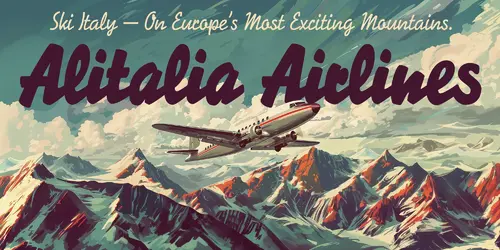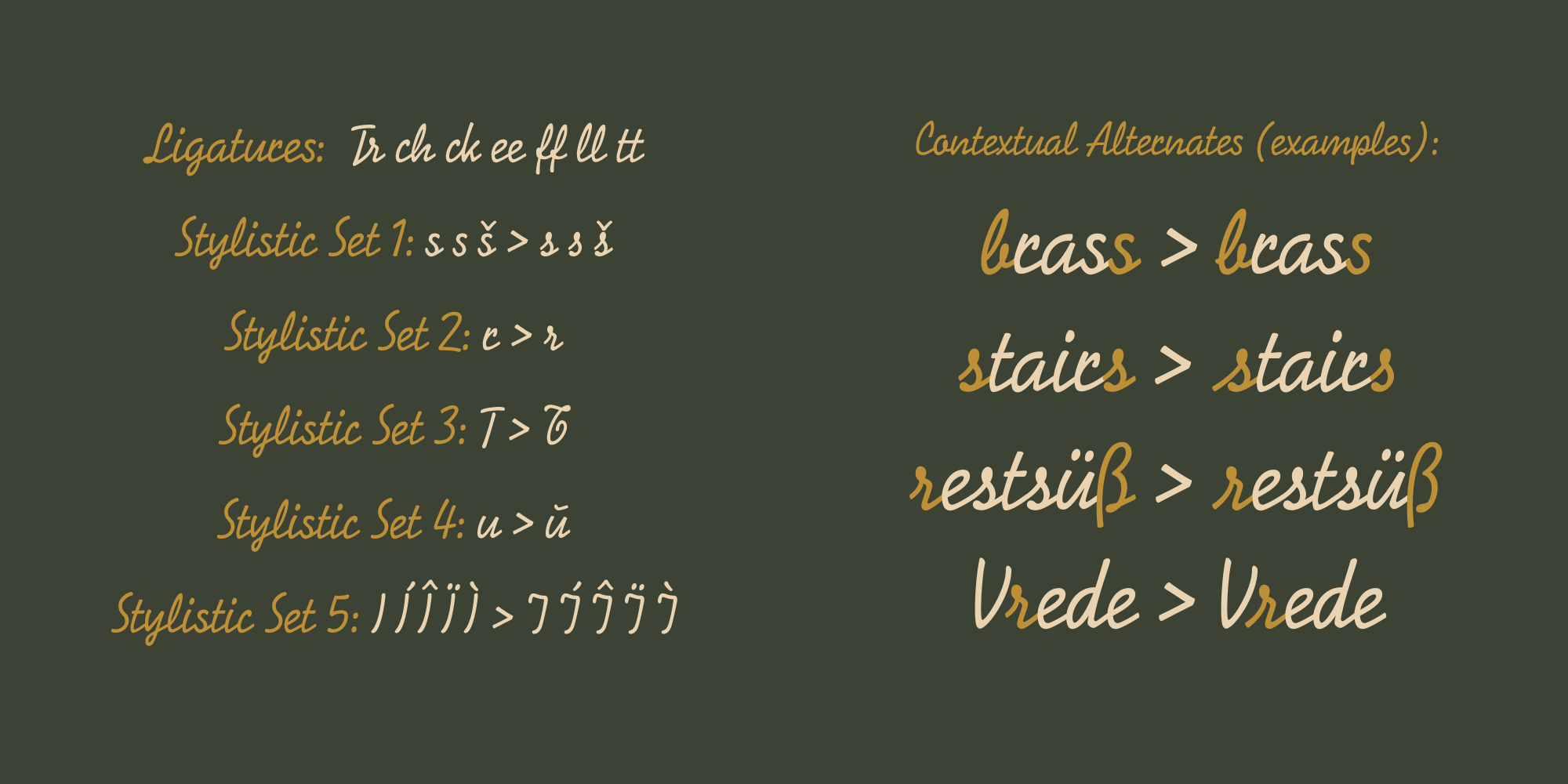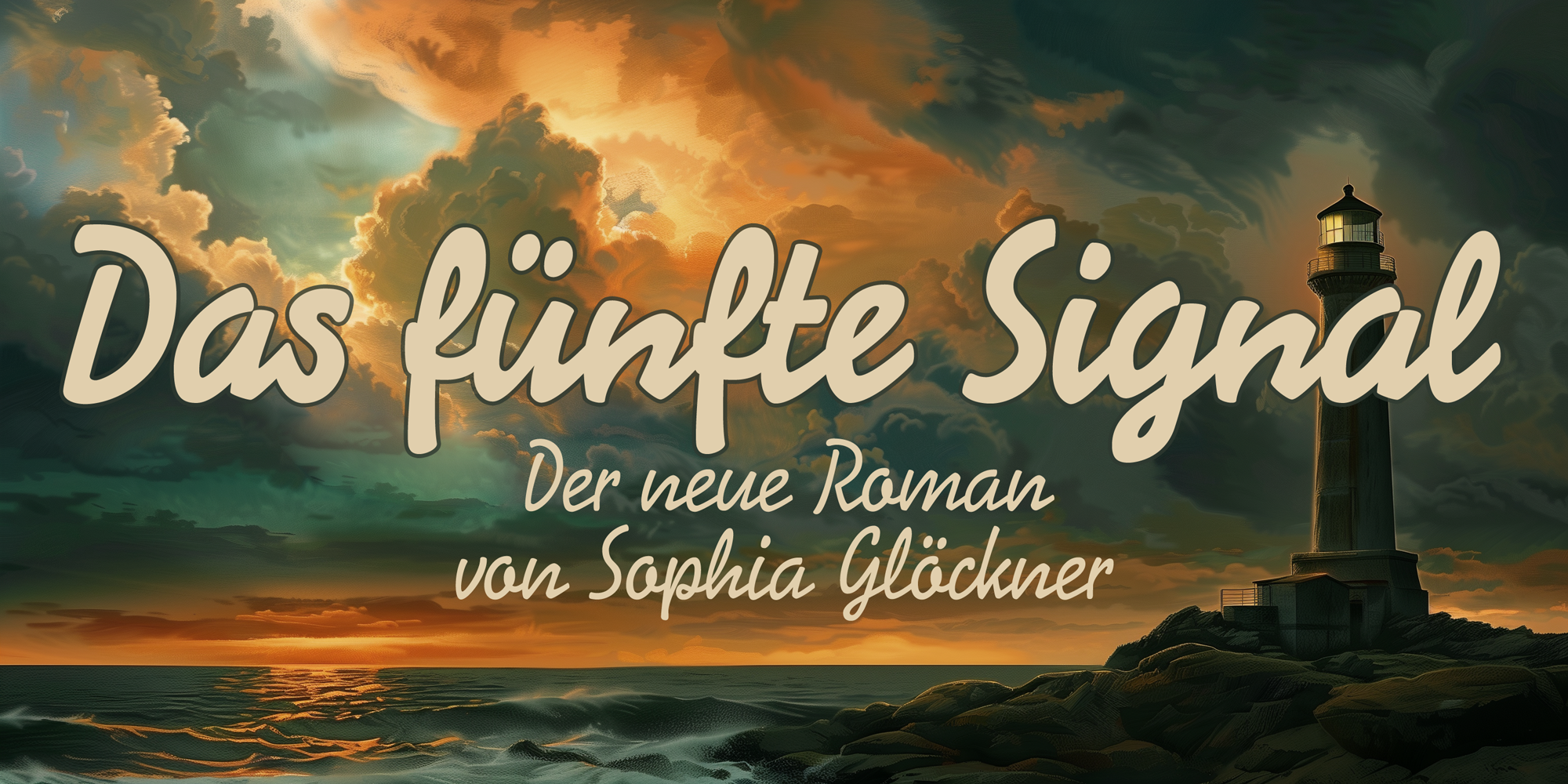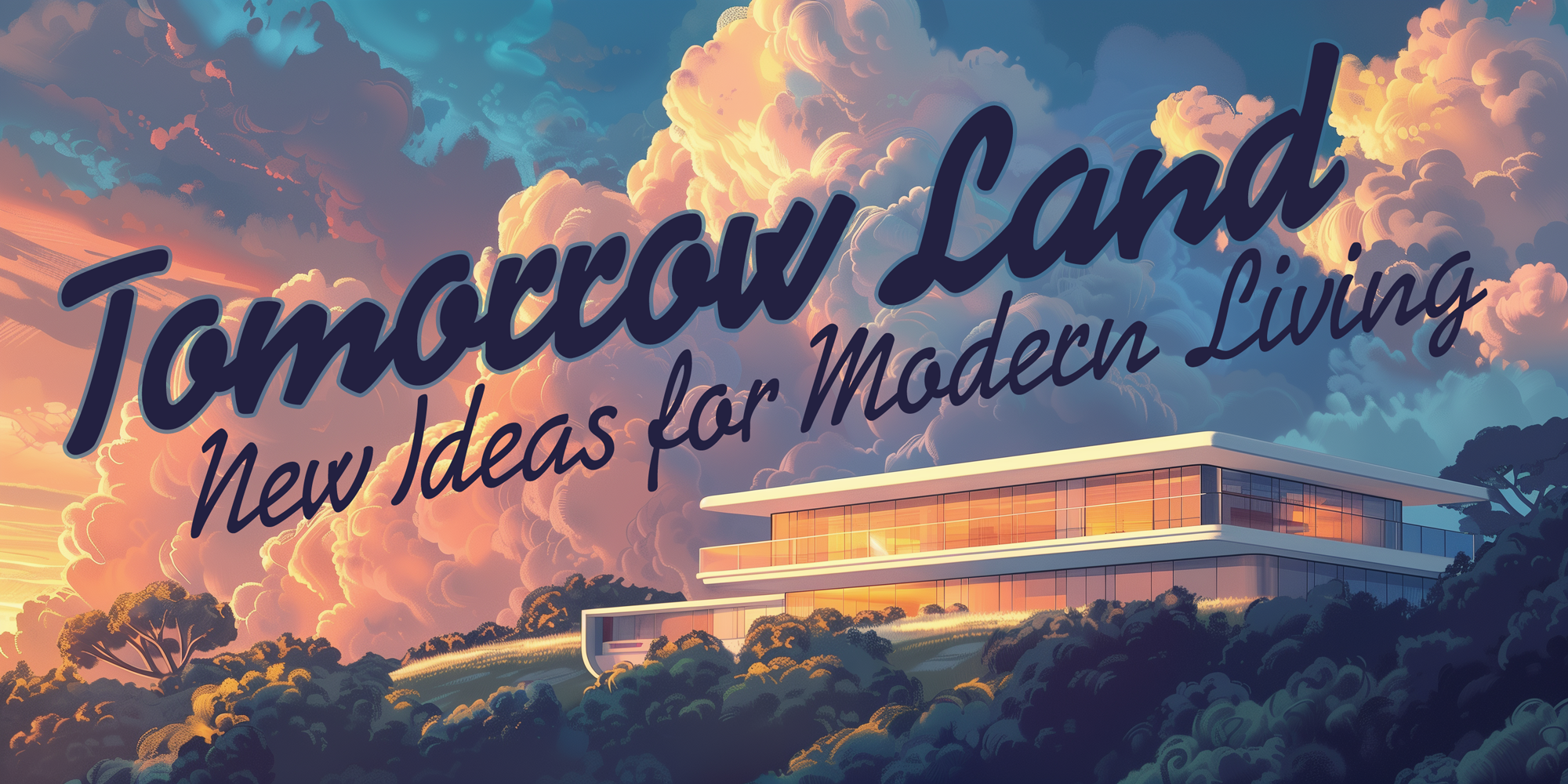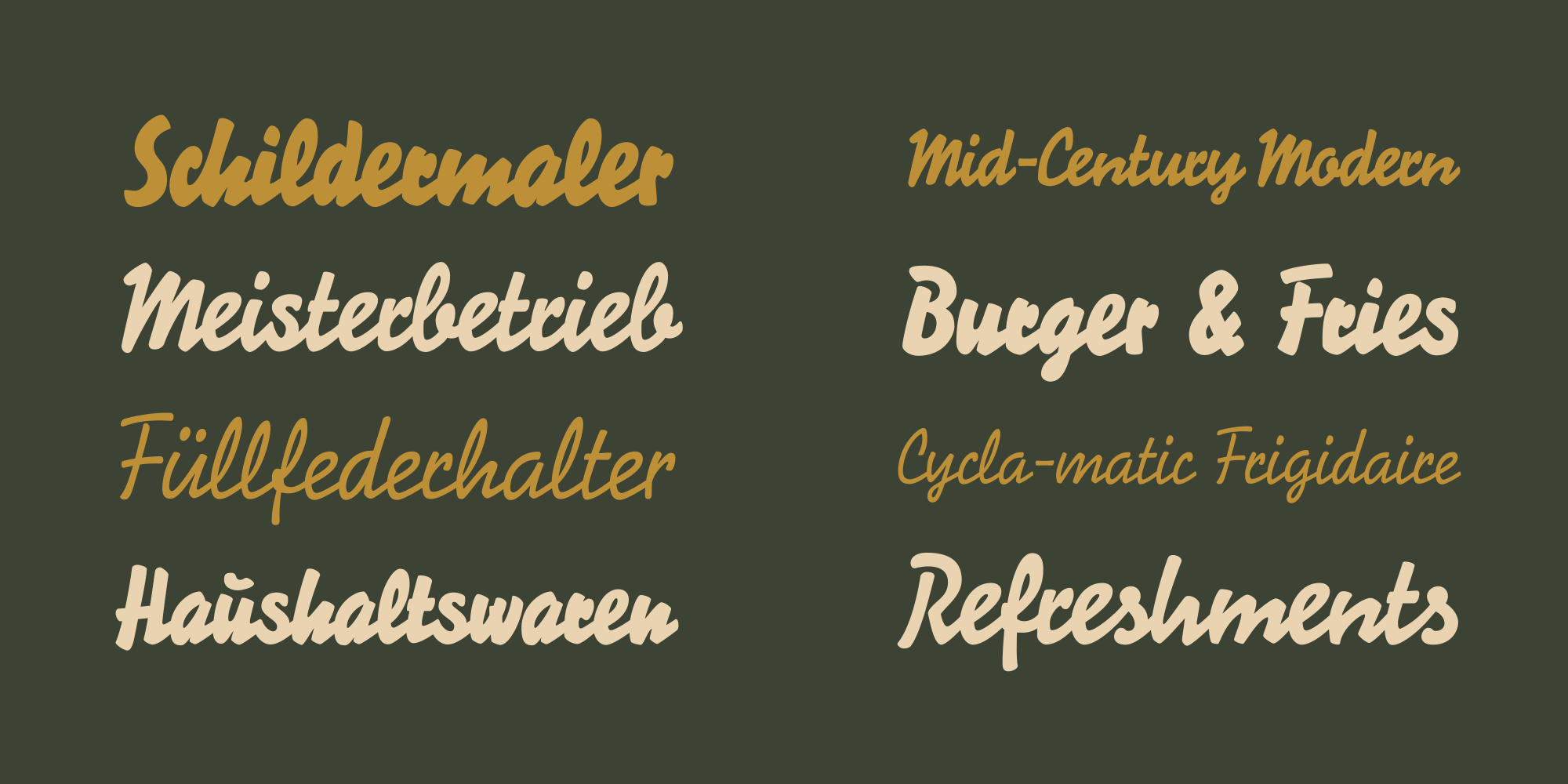
Eine Digitalisierung der Berthold-Signal-Schriften in drei Schnitten (.OTF) und alternativ als ein variabler Font.
Walter Wege, Ralf Herrmann
FDI Type Foundry